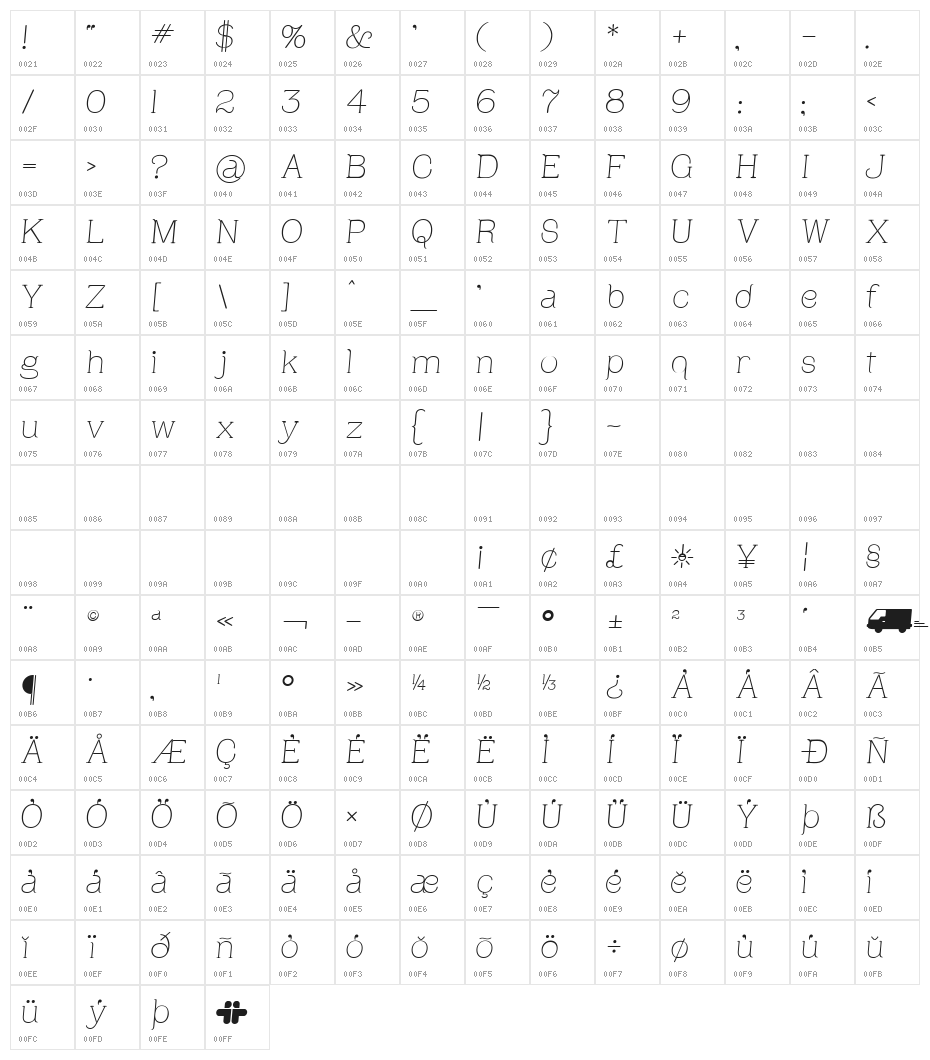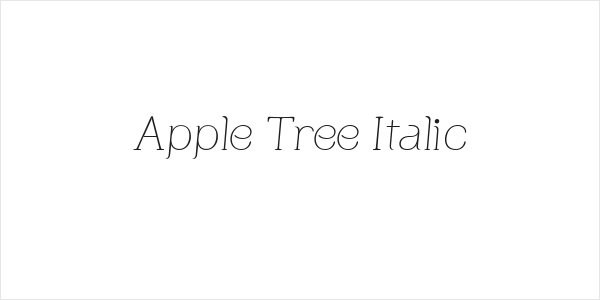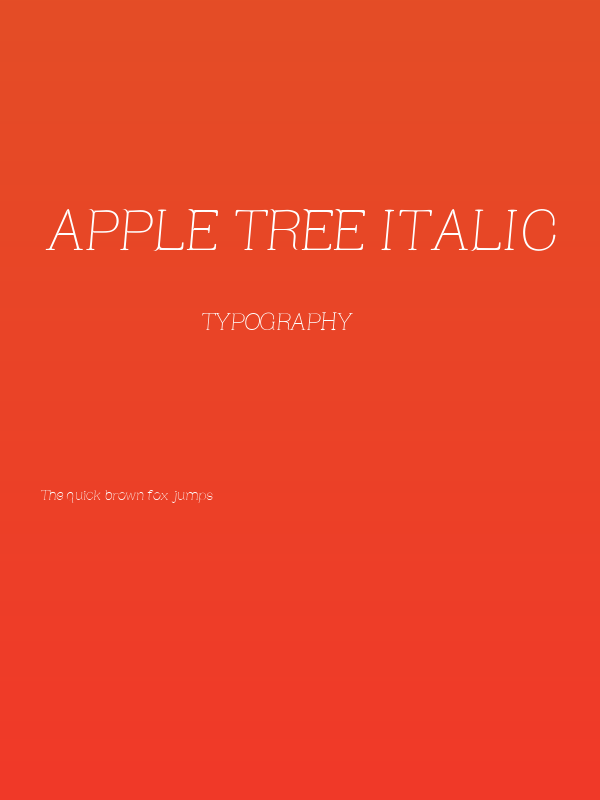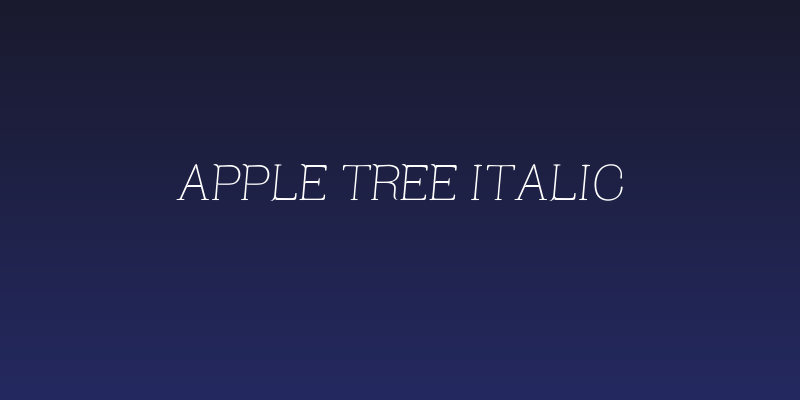
Apple Tree Italic Font
| Gesamtstil | Elegant |
| Anwendungsfall | Headlines, Invitations, Branding |
| Vorgeschlagene Projekte | Ideal for wedding invitations, elegant branding, and sophisticated editorial design. |